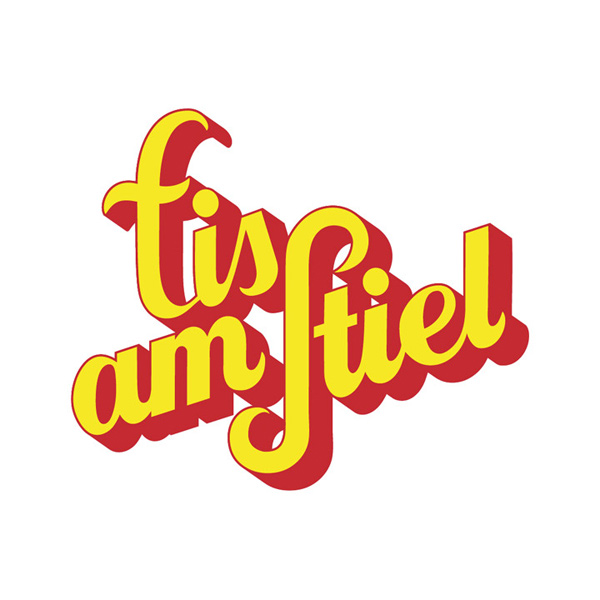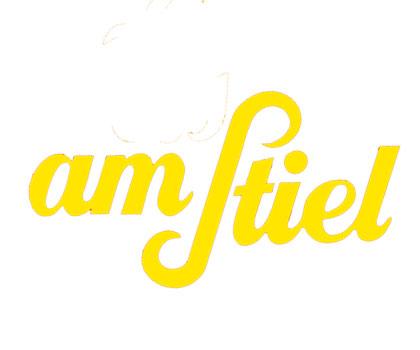
Font "Eis am Stiel"
kann mir jemand von Euch sagen wie die Schriftart von "Eis am Stil" heißt?
Nachdem das von "David Huckert | Lettering & Illustration" stammt, könnte es handgemacht sein.
Creampuff geht leicht in die Richtung, schau ich mir mal an. Danke.
Mir gefallen besonders gut die  langgezogenen Großbuchstaben bei dem Font von Huckert.
Vielleicht muss ich mich selber "dranwagen".
Nun, das ist eben kein Font